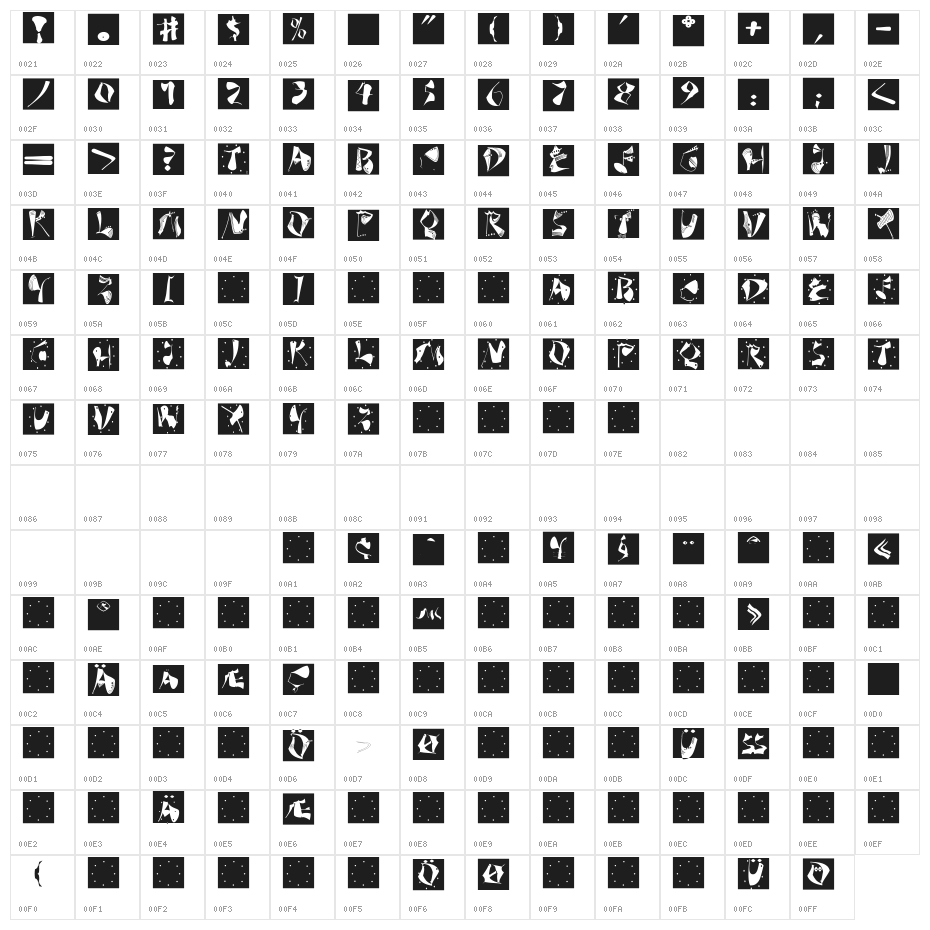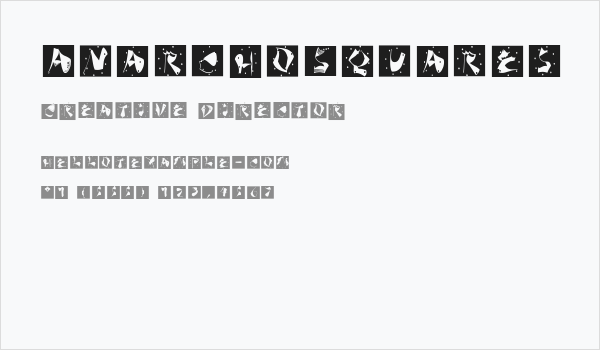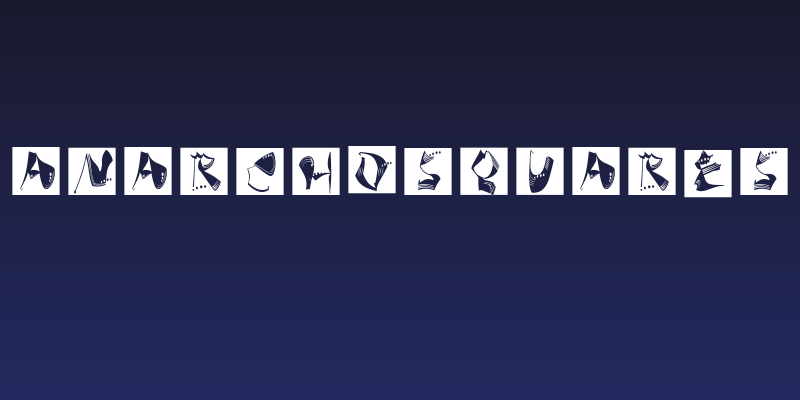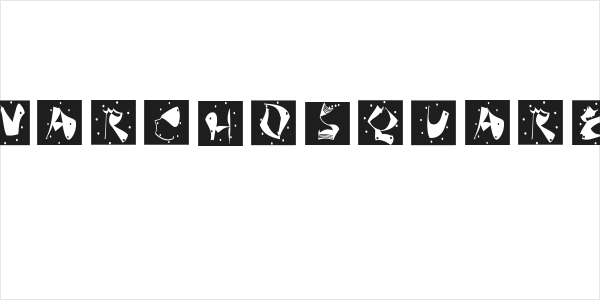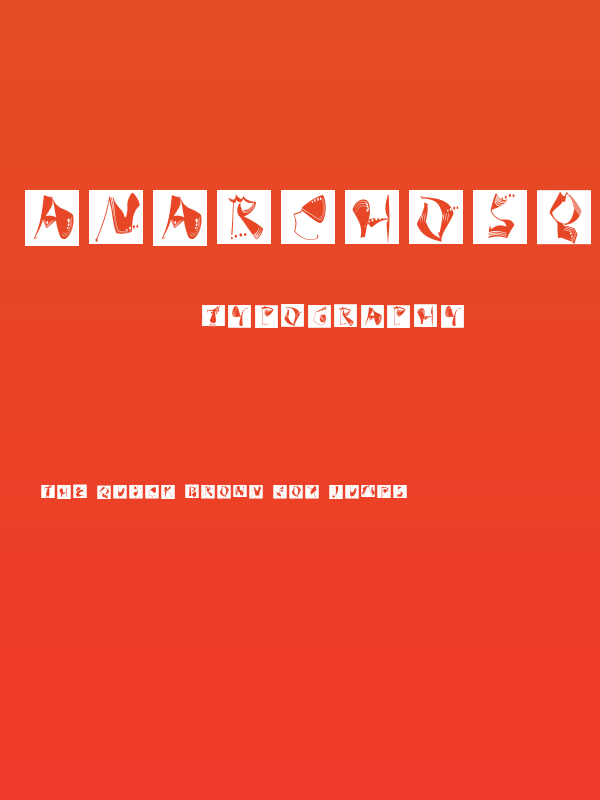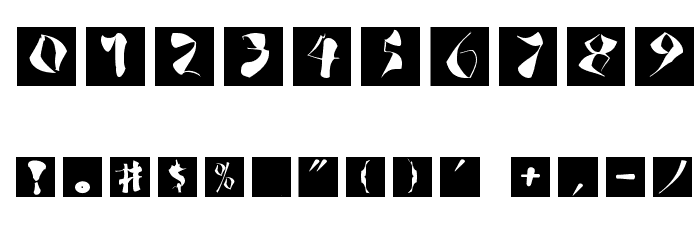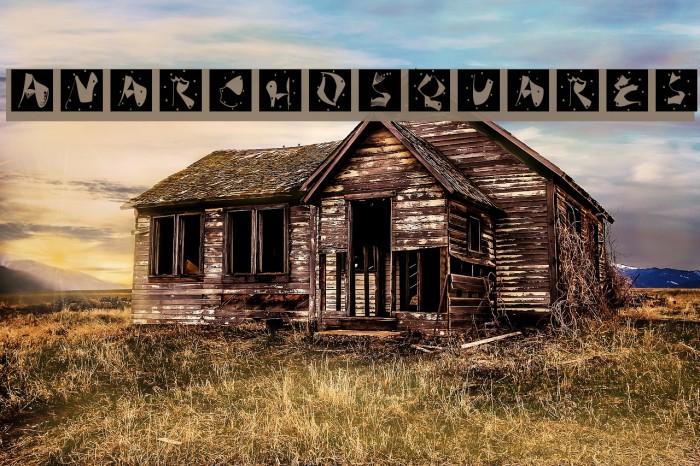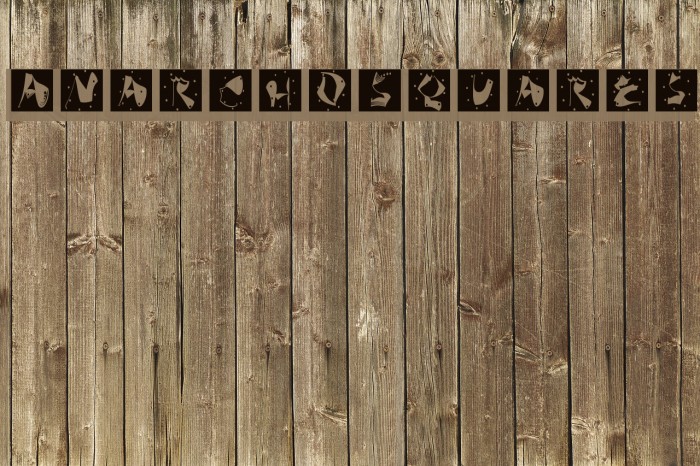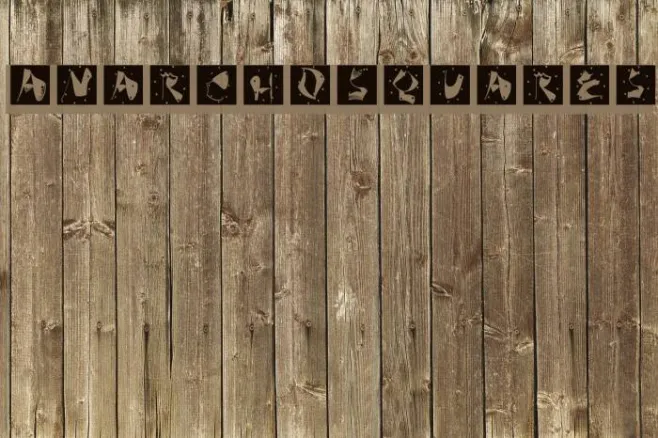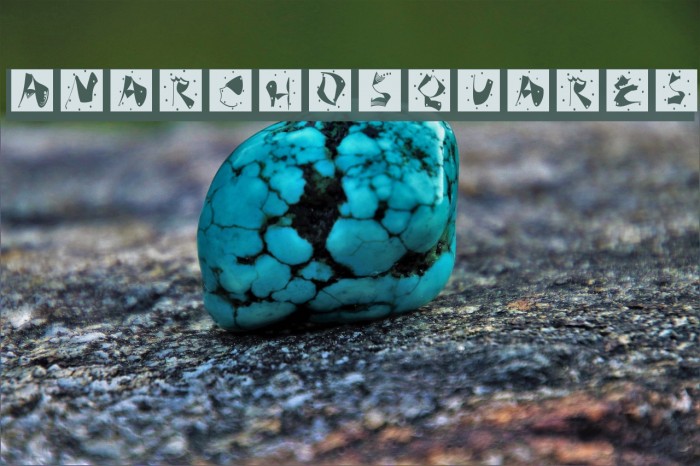
AnarchoSquares Font
| Caso d'uso | Logos, Headlines, Artistic projects |
| Progetti proposti | Ideal for album covers, posters, artistic projects, and any design requiring a bold, unconventional look. |